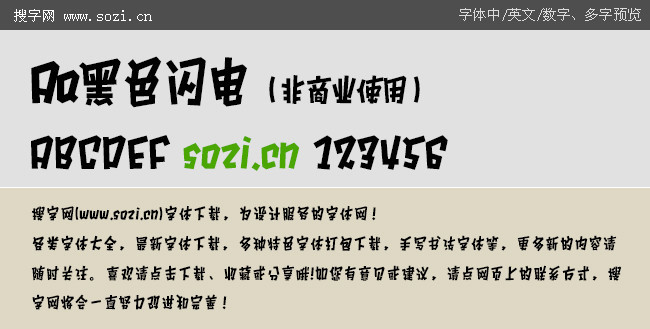
Aa黑色閃電
搜字網(wǎng)給大家提供一款A(yù)a黑色閃電(非商業(yè)使用)中文字體下載,該字體是一款個性的藝術(shù)字體,字體特點為上大下小筆畫向下收攏,筆畫筆直,方切折角,擁有如閃電一般向下劈砸的千鈞之力。適合書裝設(shè)計、包裝設(shè)計、海報設(shè)計等應(yīng)用(此字體為個人非商用版,商用可以聯(lián)系QQ:1006760504)。